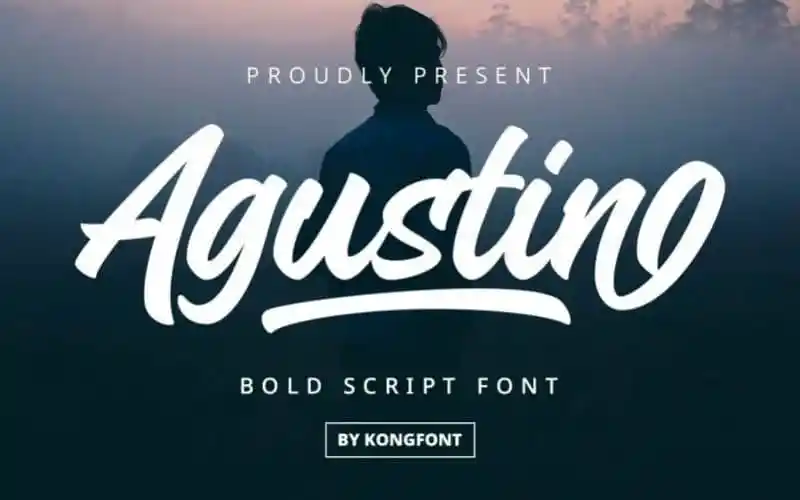
Agustin Script Font – Download Grátis
A Agustin Script Font é uma elegante fonte de calligrafia moderna criada pela Kong Font. Desenvolvida para ser estilosa e atemporal, ela oferece um toque sofisticado que se adequa perfeitamente a criações como logomarcas, rótulos de embalagens e mensagens memoráveis. Esta fonte é uma escolha ideal para projetos variados, desde rótulos digitais e arte para camisas até peças publicitárias ou cartazes. Suas letras detalhadas fornecem a capacidade de criar designs únicos, tornando-a perfeita para qualquer projeto que você possa estar trabalhando. A Agustin Script Font é um recurso gráfico indispensável para designers que buscam adicionar um toque único e criativo aos seus projetos.